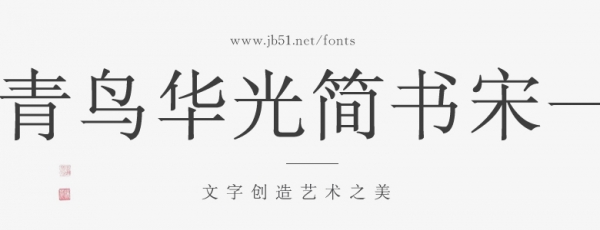
青鳥(niǎo)華光書宋字體的特點(diǎn)是筆畫流暢、收放自如,字形勻稱,線條流暢,非常適合用于書法、書籍排版、文化創(chuàng)意設(shè)計(jì)等方面。其制作采用了科學(xué)的筆畫精準(zhǔn)計(jì)算和真實(shí)的墨跡采集技術(shù),呈現(xiàn)了更加自然和優(yōu)美的書寫效果,極大地提高了閱讀體驗(yàn)。